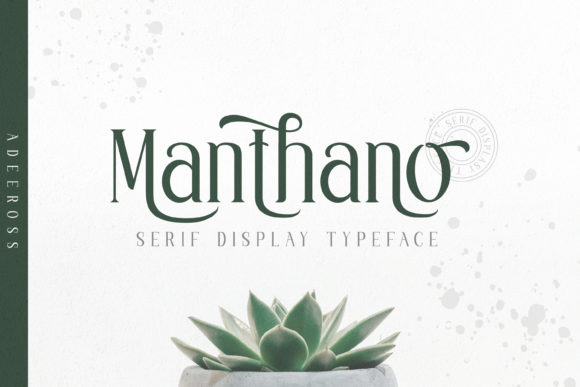
Manthano - это элегантный и современный шрифт serif, который привлечет вашу аудиторию и выделит ваш бренд.
Этот стильный шрифт может быть использован как в хосте, так и в различных контентах и проектах.
Идеально подходит для брендинговых проектов в социальных сетях, дизайна одежды, печатных цитат или даже в качестве стильного текстового наложения на любое фоновое изображение и многое другое.